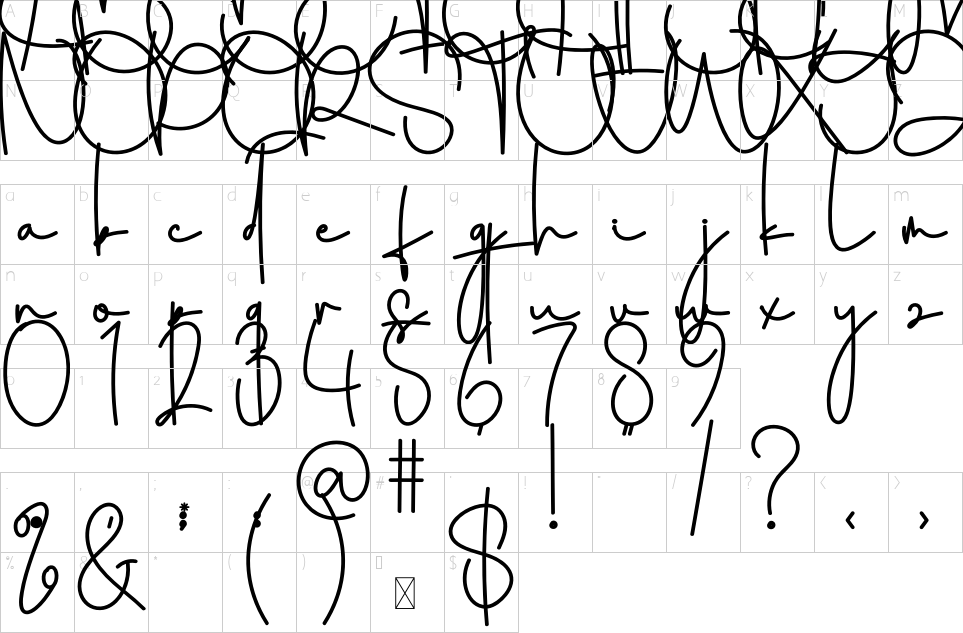
Aqui está uma descrição em português do Brasil, envolvente e natural, para a página de download da fonte ‘Aesthetic Font’: Aesthetic é uma fonte de texto ideal para aqueles que buscam um estilo moderno e sofisticado. Desenvolvida pelo designer scratchones, esta fonte foi projetada para dar vida às suas criações digitais. Ideal para blogs, sites pessoais, e até até a criação de designs gráficos, Aesthetic oferece um acabamento elegante que vai agradar qualquer designer. Com uma aparência que combina elementos modernos e clássicos, esta fonte é uma excelente escolha para quem quer dar um toque único e sofisticado a seu conteúdo online. Compre Aesthetic agora e enriqueça suas criações com um estilo único e moderno. Disponível tanto para Windows quanto para Mac, Aesthetic é uma opção confiável para qualquer designer.